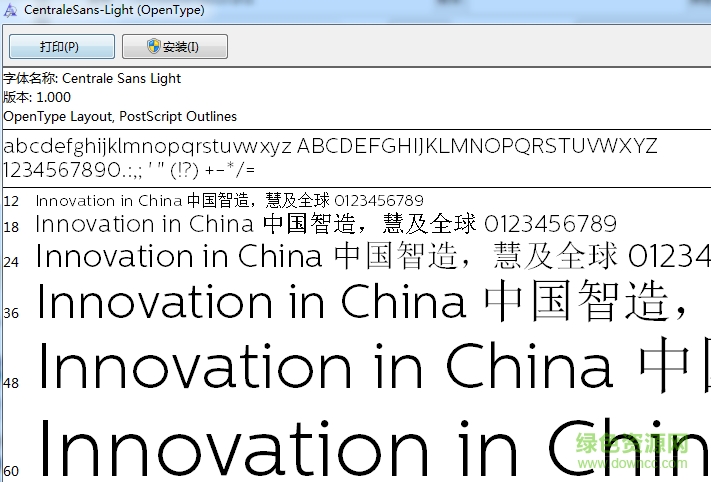
CentraleSans字體是一款非常具有個(gè)性的英文字體,字體擁有非常柔美的線條,在廣告設(shè)計(jì)上能夠輕松彰顯自己個(gè)性,非常適合用于平面設(shè)計(jì)行業(yè),喜歡的朋友就來綠色資源網(wǎng)下載使用吧!
CentraleSans字體是一款個(gè)性英文字體,字體能夠幫助用戶提現(xiàn)自己的個(gè)性,彰顯不一樣的用途,有需要的朋友就趕快來綠色資源網(wǎng)下載吧!